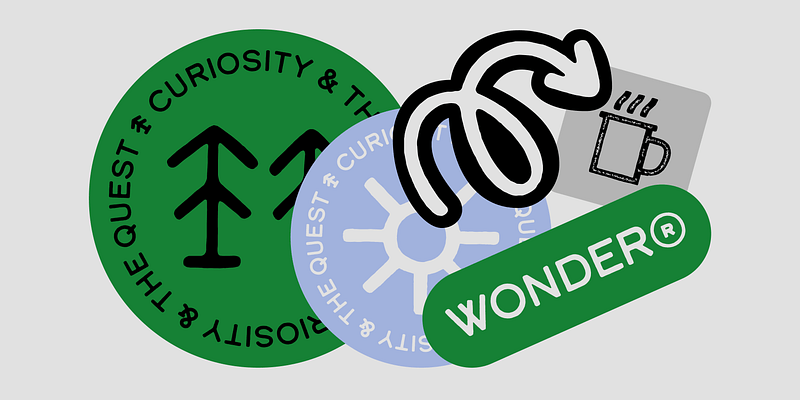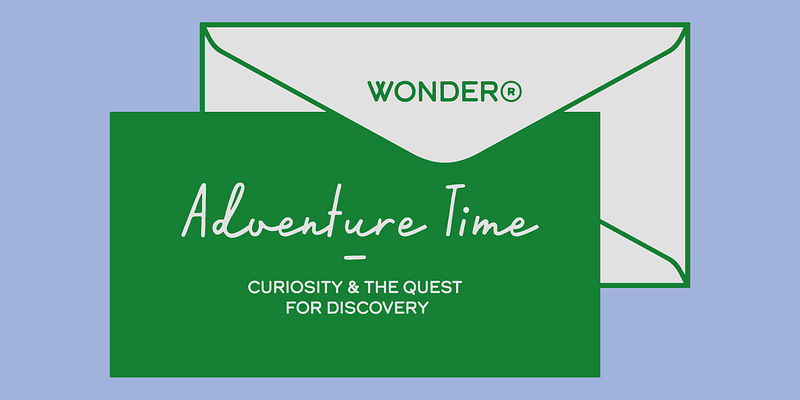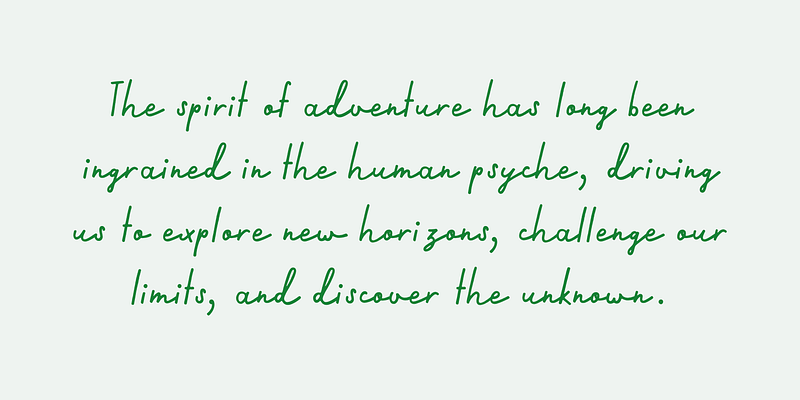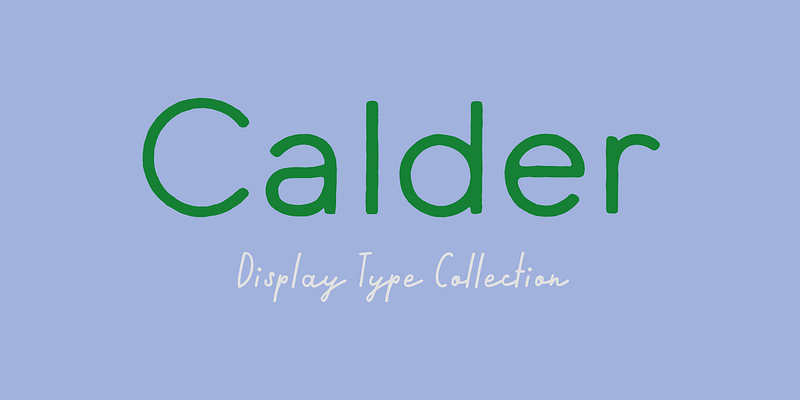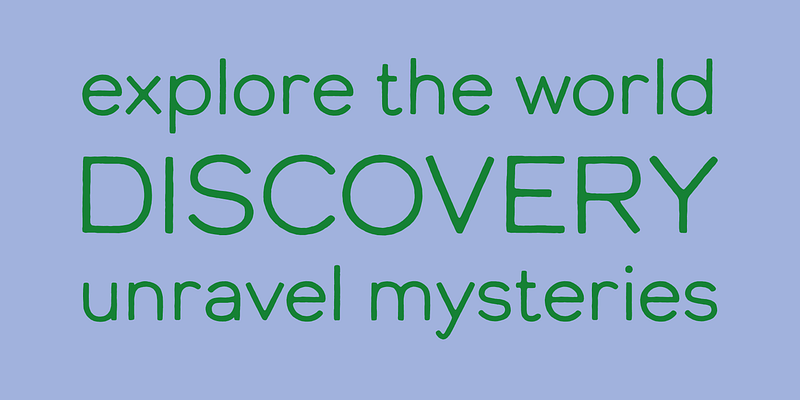
Calder es una colección de tipos de letra para pantalla. Incorpora 10 estilos y ofrece dos voces distintivas: una escritura juguetona semiconectada y una selección de sans serif sutiles pero auténticas. Diseñados para complementarse entre sí, ofrecen una herramienta visual única y atractiva. Calder Script, Calder LC y Calder LC Grit están disponibles tanto en mayúsculas como en minúsculas, mientras que el resto de la colección está disponible únicamente en mayúsculas. Inspirada por la búsqueda de actividades al aire libre, Calder comenzó como una experiencia personal y un esfuerzo por expresar y compartir el espíritu de aventura conectado con este movimiento renovado y en crecimiento.